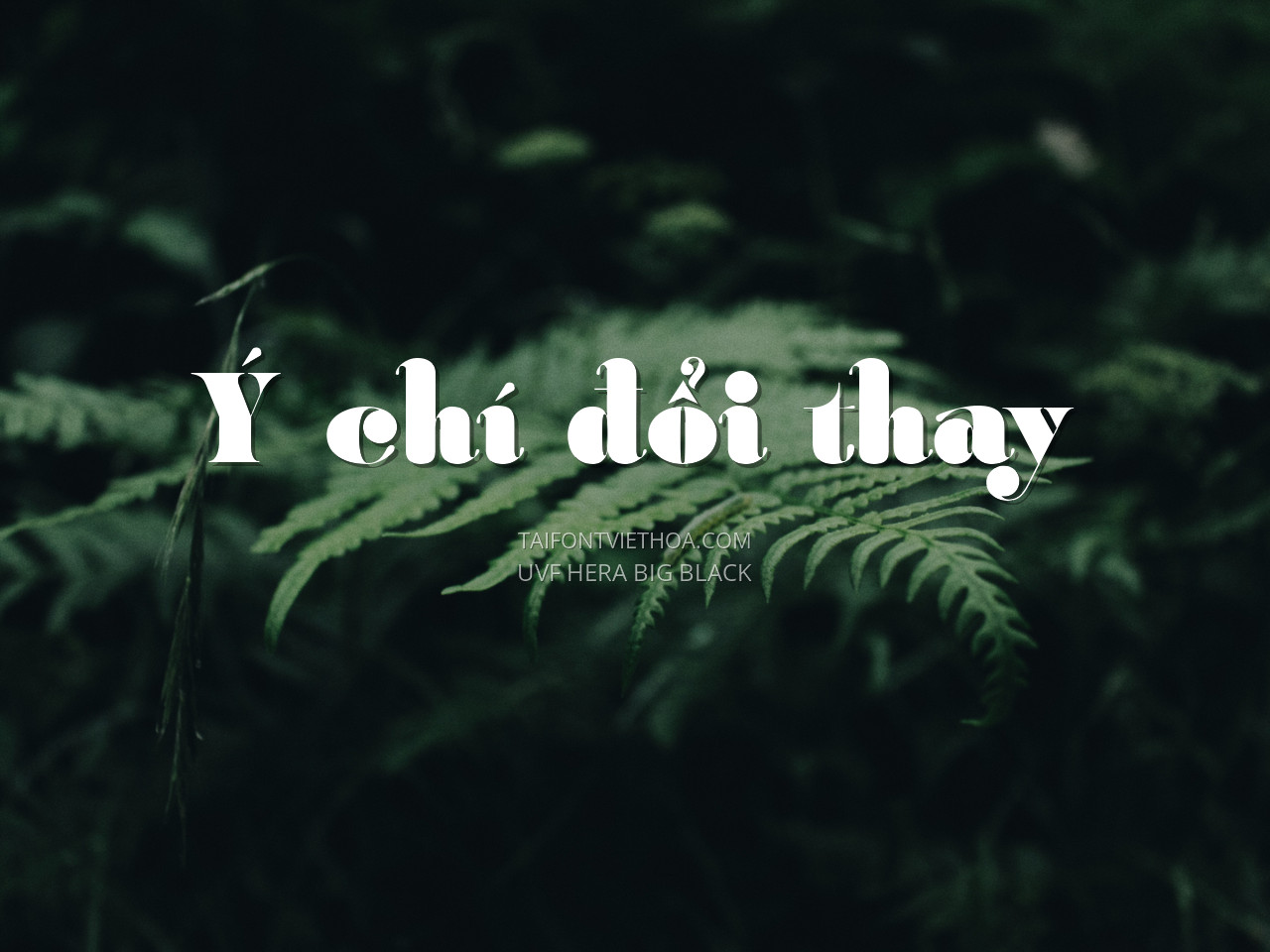
Font việt hóa UVF Hera Big Black
Giới thiệu về font UVF Hera Big Black
UVF Hera Big Black là một font chữ serif ấn tượng với thiết kế đậm nét, mang đến sự quyền lực và sang trọng cho bất kỳ sản phẩm thiết kế nào. Lấy cảm hứng từ phong cách biên tập cao cấp và thời trang đương đại, font này kết hợp giữa nét cổ điển của serif và độ dày mạnh mẽ để tạo nên hiệu ứng thị giác mạnh. UVF Hera Big Black đã được sưu tầm và chia sẻ bởi thành viên Font Chuẩn, đồng thời được taifontviethoa.com chọn lọc để ứng dụng trong các thiết kế thương hiệu, biên tập thời trang và truyền thông cao cấp.
Đặc điểm thiết kế và ứng dụng của UVF Hera Big Black
Font có cấu trúc serif truyền thống nhưng được tăng cường độ dày một cách rõ rệt, tạo cảm giác dứt khoát và mạnh mẽ. Đường cong mềm mại đi cùng chân chữ vững vàng mang lại nét đẹp hài hòa giữa sự nữ tính và quyền lực. UVF Hera Big Black hỗ trợ tiếng Việt đầy đủ, mang lại trải nghiệm đa ngôn ngữ hoàn chỉnh cho người dùng.
Ứng dụng lý tưởng: thiết kế tiêu đề tạp chí, branding thời trang cao cấp, ấn phẩm truyền thông, poster quảng cáo hoặc bìa sách nghệ thuật. Ngành nghề phù hợp: thời trang, mỹ phẩm, nội thất cao cấp, xuất bản, quảng cáo và thiết kế thương hiệu sáng tạo.